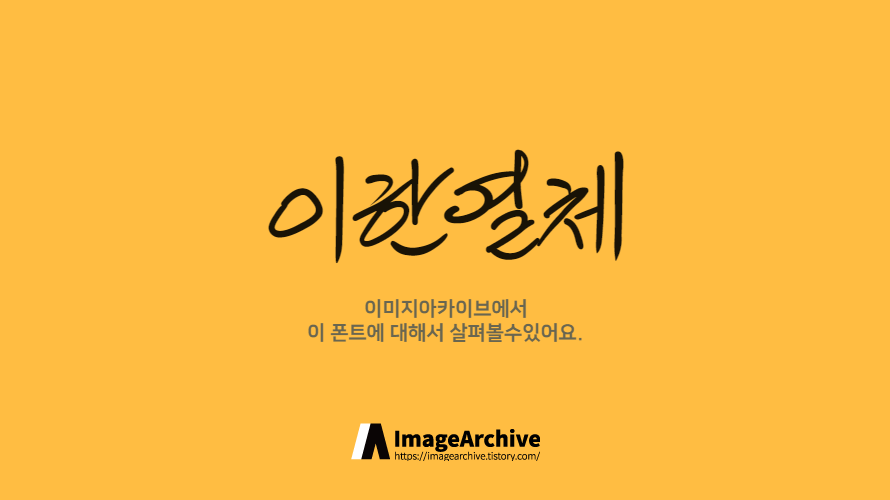
이한열체의 특징
이한열체는 1987년 6월 민주항쟁의 상징적인 인물인 이한열 열사를 기리기 위해 제작된 폰트입니다. 주요 특징은 이한열 열사의 손글씨를 바탕으로 한 따뜻하고 인간적인 느낌을 전달하는 서체입니다. 필기체와 가까운 자연스러운 곡선이 특징이며, 민주화 운동의 상징성을 담아 자유와 평등, 열정을 표현합니다. 무료로 배포되며, 다양한 용도로 사용할 수 있어 사회적 메시지나 기념 프로젝트에 자주 사용됩니다.